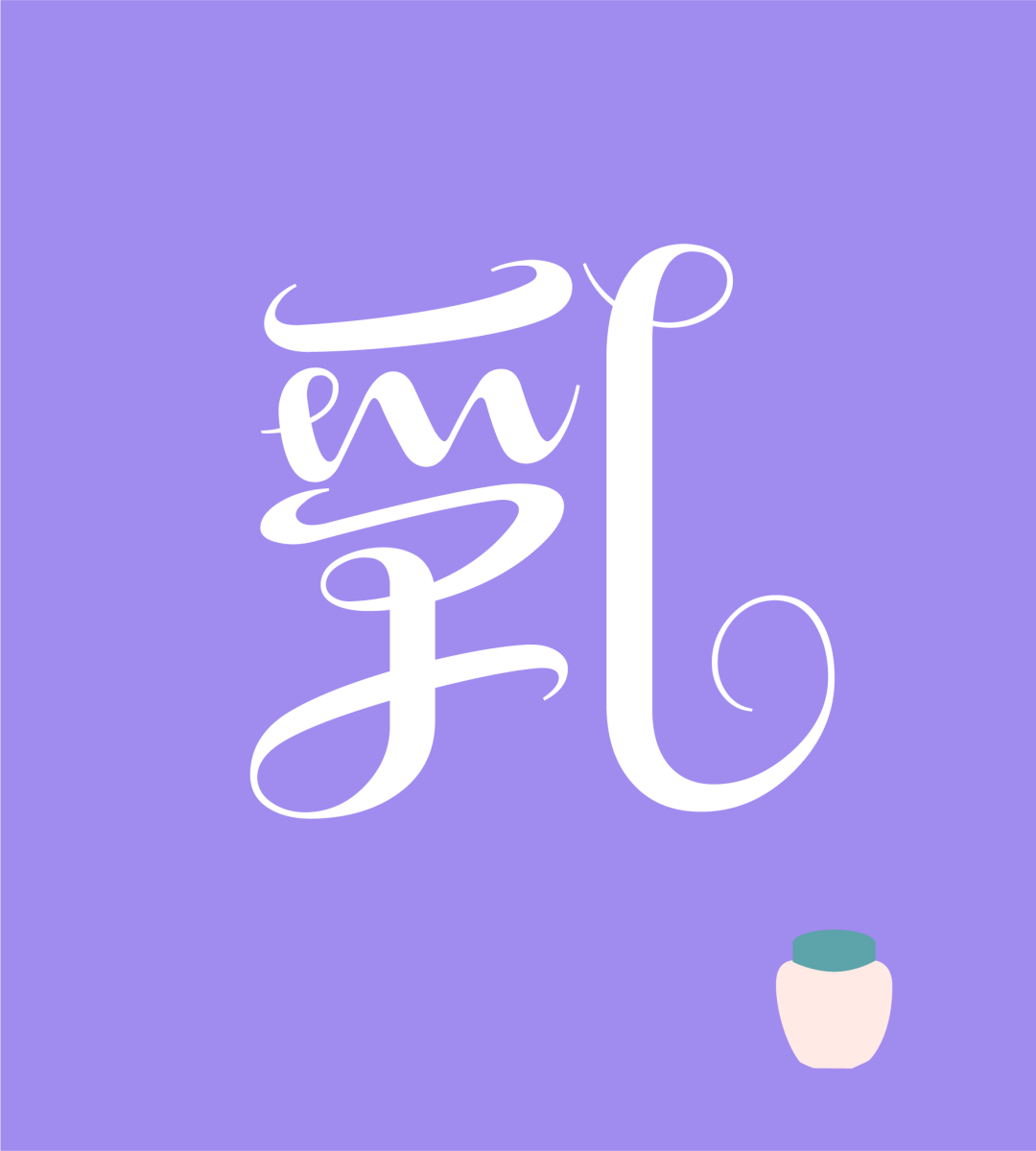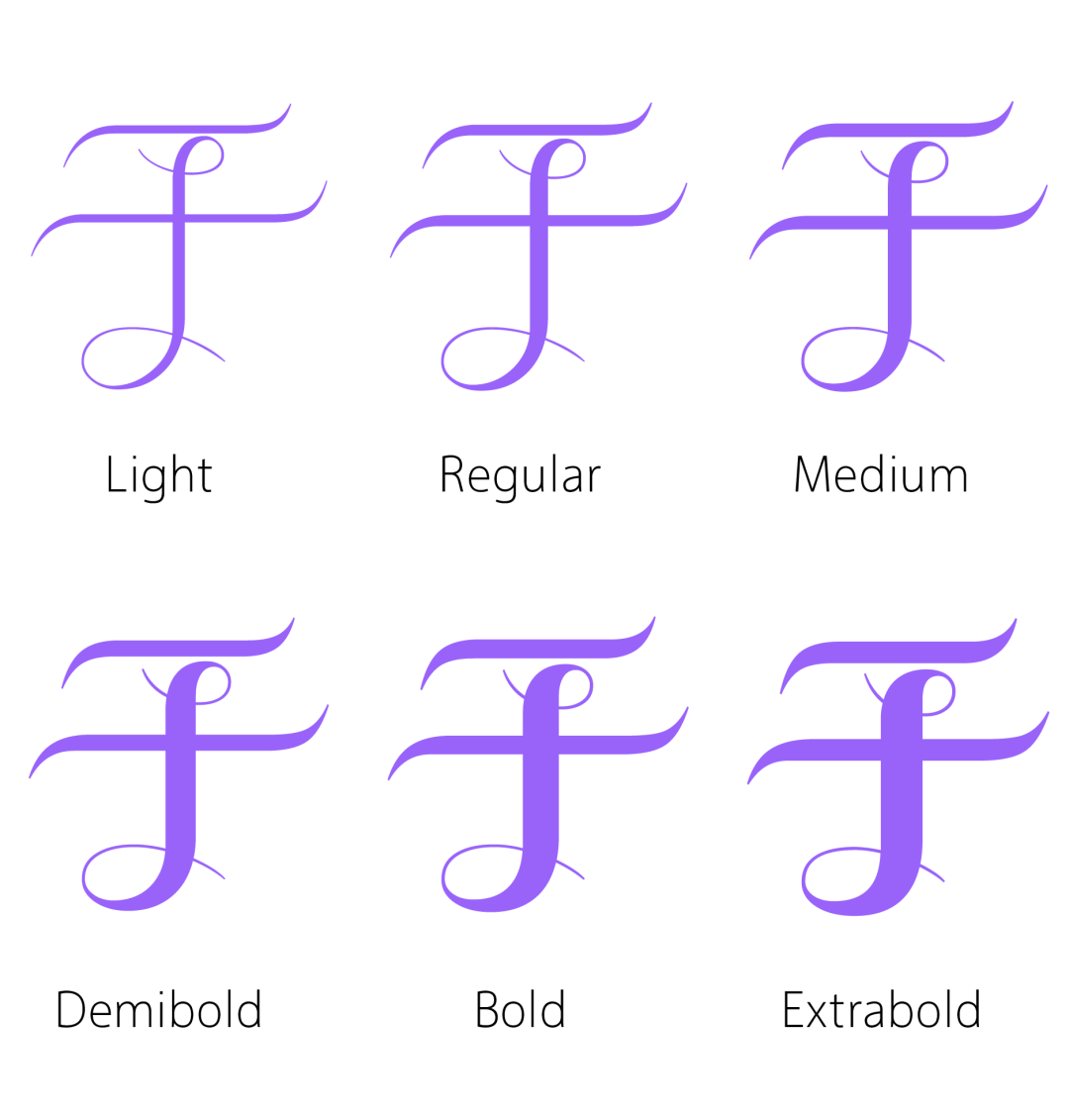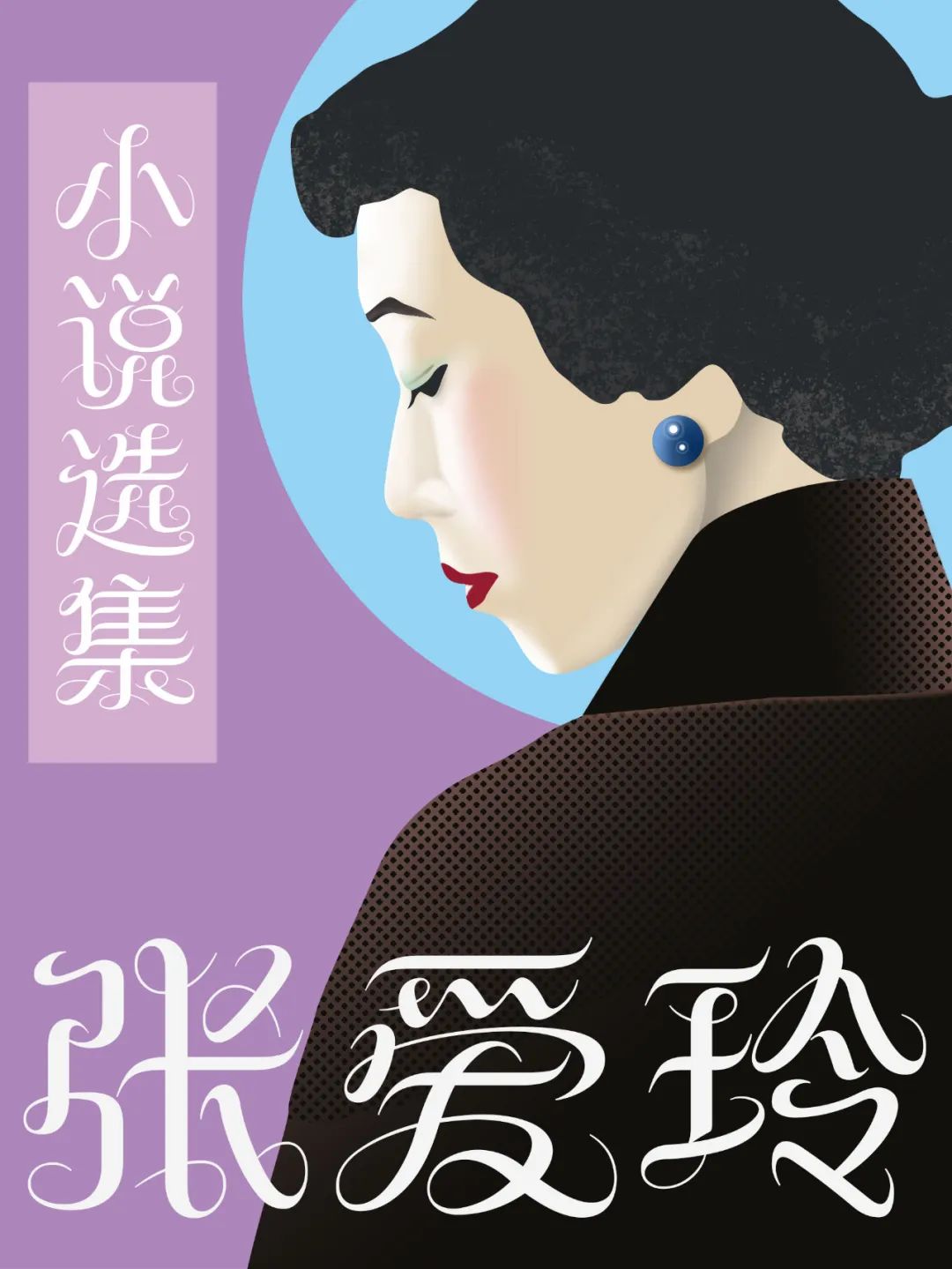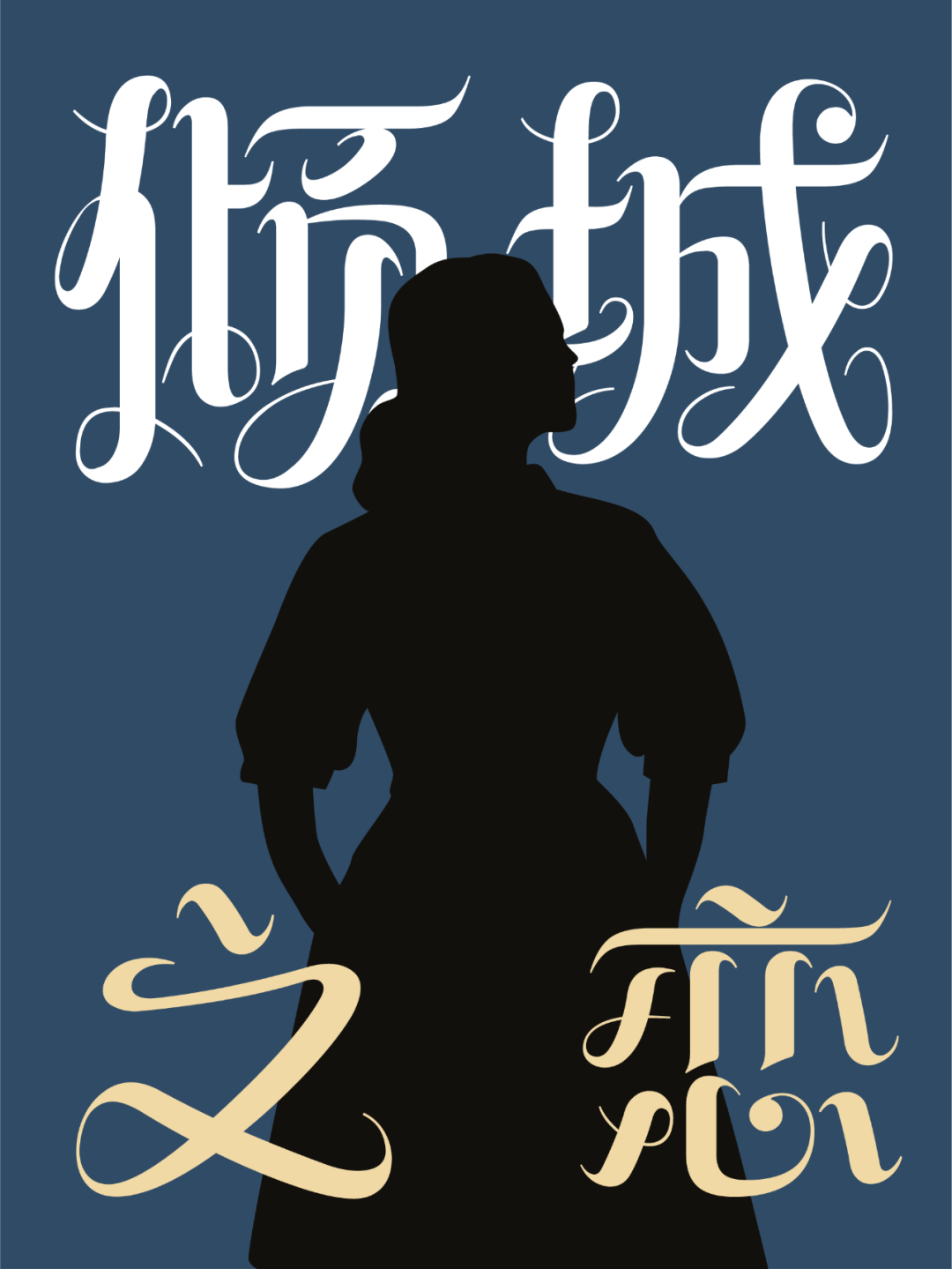
方正纤舞体家族
字体品牌: 方正字库 设计师:郭炳权 字体分类:创意字体 字体属性:精品字 字符集:大陆简体(GB2312-80)、简繁扩展(GBK) 发布时间: 2020
纤舞体是以拉丁文“Script”形态演绎的中文花写字体。“Script”字体在西方非常普遍和流行,但在笔画繁复的中文字体中演绎难度甚高。纤舞体风姿绰约,曼妙动人,适合高档时装、化妆品、手袋、鞋类等包装宣传以及纤体美容类产品宣传,也适合生日卡、情人卡、圣诞卡和各种贺卡设计等等。
方正纤舞体的创作灵感来源于英文草书(Script Font),这是一种基于手写而形成多变且流畅的字体曲线的风格字体,字母之间一般具有明显的连笔笔法,有时一个完整单词的字母间能联结为一个复杂的整体。这些字体通常被应用于邀请函和正式文件,以营造出高贵典雅的感觉。
美国商业文书中的英文草书手写体应用示例,上图中的这种书体被称为Spencerian ScriptScript 字体的历史源远流长,在西文设计、应用领域非常普遍和流行,但对于笔画繁复的中文字体来说,演绎难度甚高,少有人尝试。资深字体设计师郭炳权首次把Script 手写字体风格融入中文字体设计中,将复杂的中文笔画巧妙地化为屡屡游丝。经过两年多时间反复地修改和校对,最终完成了方正纤舞体的开发,国内首款中文Script 手写风格字体正式诞生。
方正纤舞体的设计开始于2017年10月,为了使每一个部件的造型、弧线、角度都达到完美的状态,与其他部件搭配时能够协调统一,郭炳权老师率领其团队对每一个部件的设计都进行了反复的试验和调整,最终完成了3152个字体部件的设计。
纤舞体字体部件设计巧妙,笔画如游丝般细腻,曲线粗细变化流畅自然。其竖、勾修长延绵,如美人之延颈秀项,亭亭玉立;横、折曲回婉转,如女子之轻逸步态,流风回雪,呈现出优美、动态、舒展的字体风貌。
纤舞体的点画不独自成立,往往与其他笔画相连接,加强整体感,其造型如宛转悠扬的音符,增添几分动态的美感。
方正纤舞体运用悠扬连贯的曲线取代了字体笔画的转折,笔势连绵起伏,像一丝浮游在空中不知从何处飘来的飞絮,整体上笔势连贯、气韵飞扬,充满跃动感。
字体空间布局巧妙,结构匀称稳定,笔画疏密严谨,具有节奏感;各部件之间的穿插避让合理、各得其所,各文字之间彼此协调、风格统一,具有醒目的视觉效果。
方正纤舞体作为作为一款面向女性群体的手写风格字体,其风格高贵典雅、动感活泼、情感饱满、装饰度极高,充满时代感和跃动感,可广泛应用于海报设计、商业广告、礼品贺卡、书籍装帧、LOGO标志等。#书籍封面#
郭炳权现年74岁,籍贯广东省南海县。九岁开始临摹王羲之字帖,而后兼习楷、隶、篆等书体。1967年,考入香港美专设计学院,专攻广告设计和字体设计;毕业之后,进入香港帝国广告公司任字体设计员,随后在澳洲幸运广告集团任美术主任,曾任教于香港大一设计学院,教授中文字体设计。